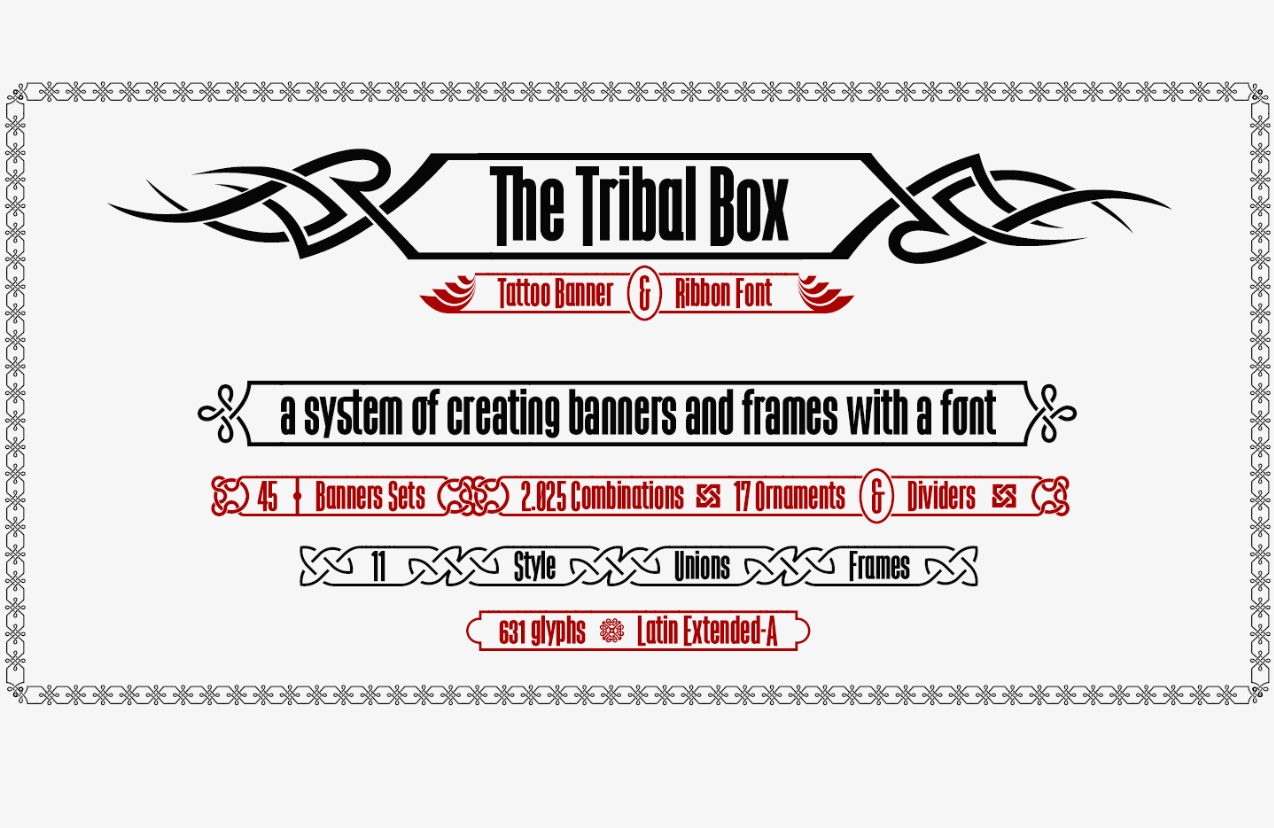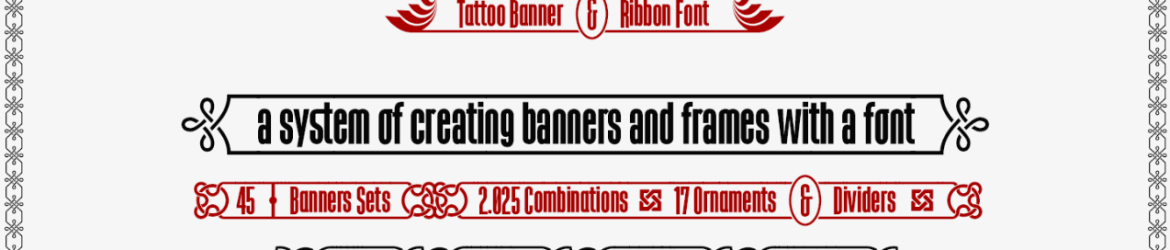
A fonte “The Tribal Box” é uma seleção única entre as fuentes retrogames para designers digitais. Sua tipografia simétrica compacta oferece um aspecto robusto e futurista, perfeito para estilos retro ou artesanais modernos. Inclui um sistema de ligaturas OpenType que permite a criação de banners e molduras com uma variedade de opções, inclusive as famosas letras digitais do estilo tatuagem. Além disso, inclui um guia completo em formato PDF para melhorar sua experiência ao usar e aplicar a fonte. O designer defharo trouxe esta fonte cheia de personalidade através de seu trabalho cuidadosamente detalhado, garantindo que ela seja não apenas uma opção funcional, mas também uma escolha inspiradora. Com um design moderno dentro de uma atmosfera vintage e futurista, “The Tribal Box” é perfeita para criações que combinam elegância com carácter forte. Para versões comerciais da fonte, adicionou mais recursos, incluindo a introdução de um símbolo Bitcoin único e uma gama mais ampla de caracteres. Esses detalhes extras tornam “The Tribal Box” ainda mais adaptável para ambientes onde você deseja criar um impacto visual forte ou personalizar elementos gráficos de maneiras criativas. A fonte é perfeitamente adequada tanto para projetos pessoais quanto para uma ampla gama de aplicações comerciais, garantindo que seja uma escolha atraente e versátil para qualquer designer em busca de um design único com poder.